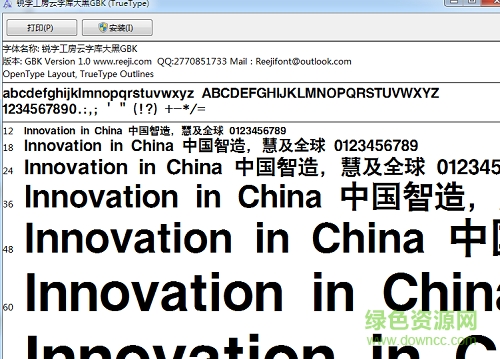
cloudheidagbk字体又叫锐字云字库大黑体gbk,该字体结构严密,字形端庄,笔形粗细相等,醒目易看,非常实用,在PPT上显示效果良好,需要的朋友欢迎在绿色资源网下载!
粗细为较粗,比黑体粗,常用于标题,导语,标志,适用于标题或需要引起注意的醒目按语或批注,用于品牌设计,互联网Aapp与软件内嵌使用,图文排版等汉字使用的广泛范围!